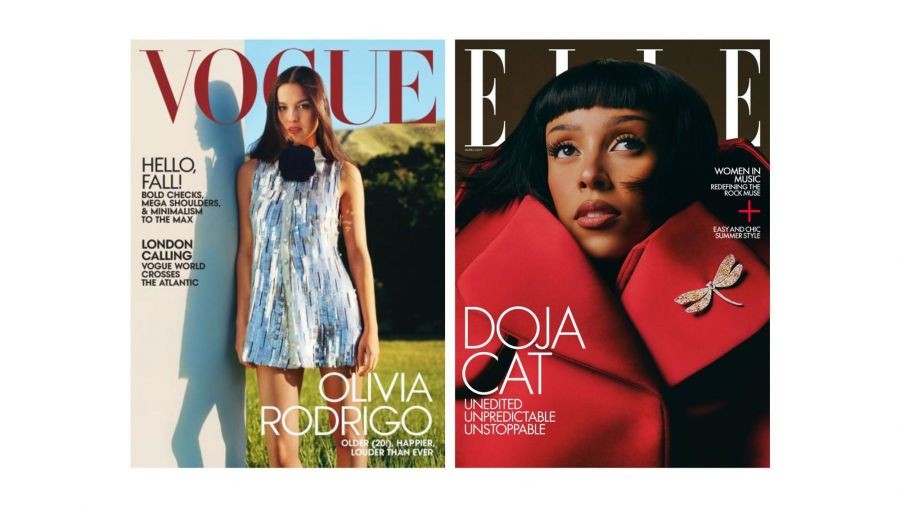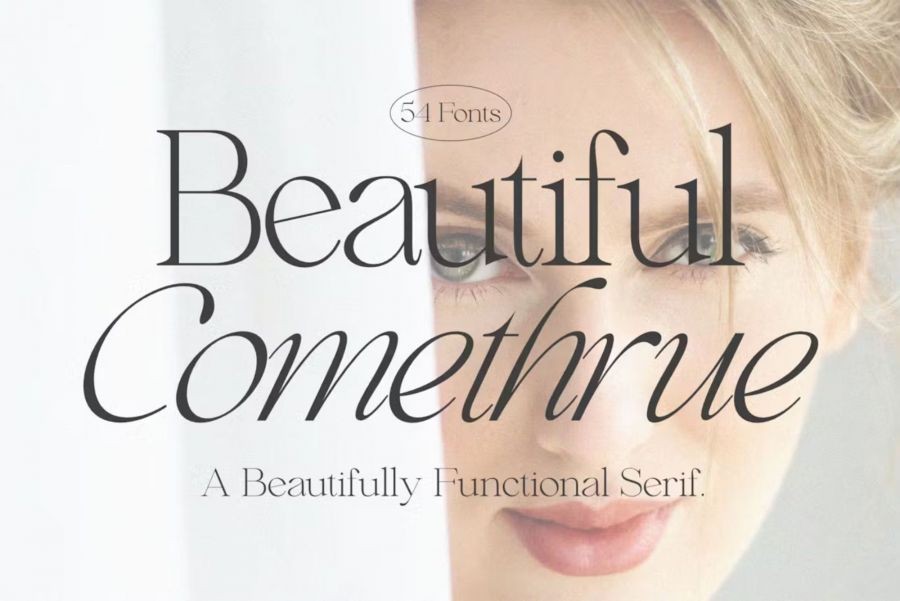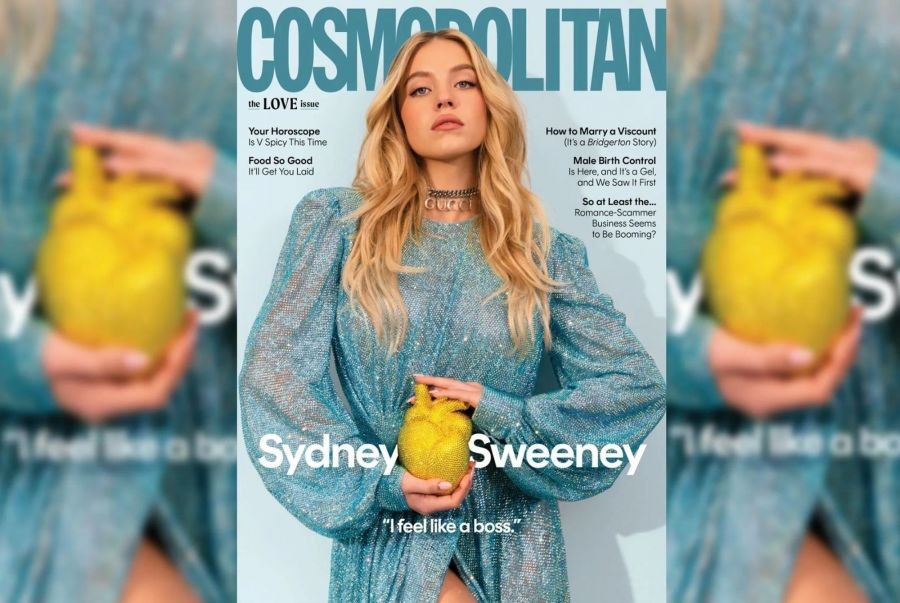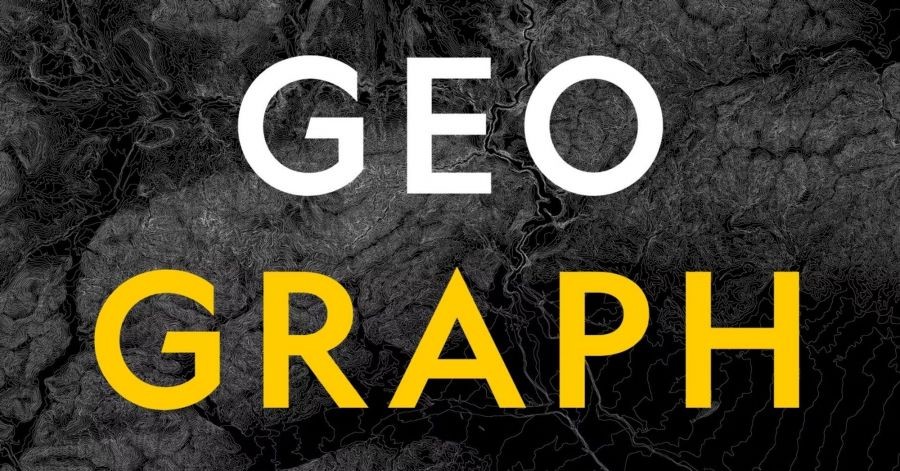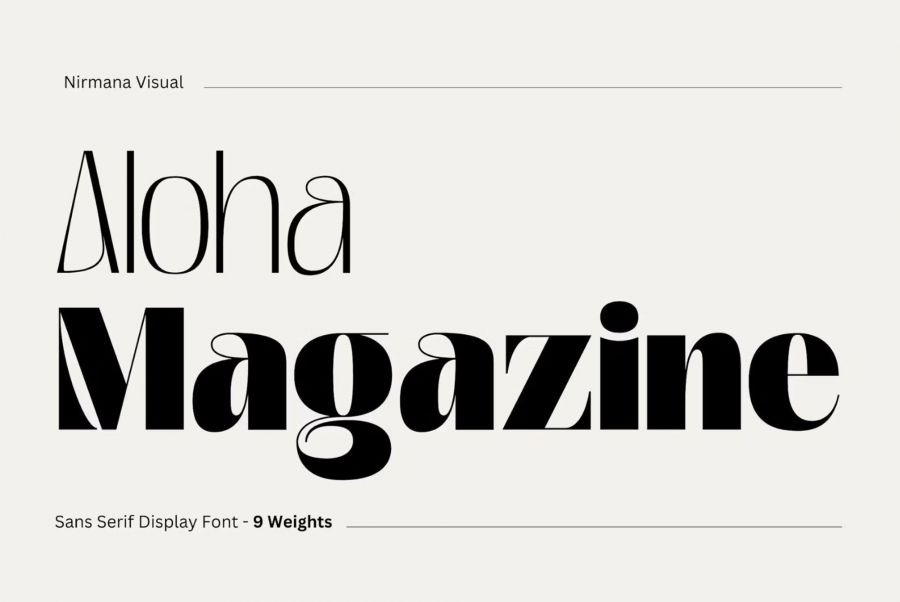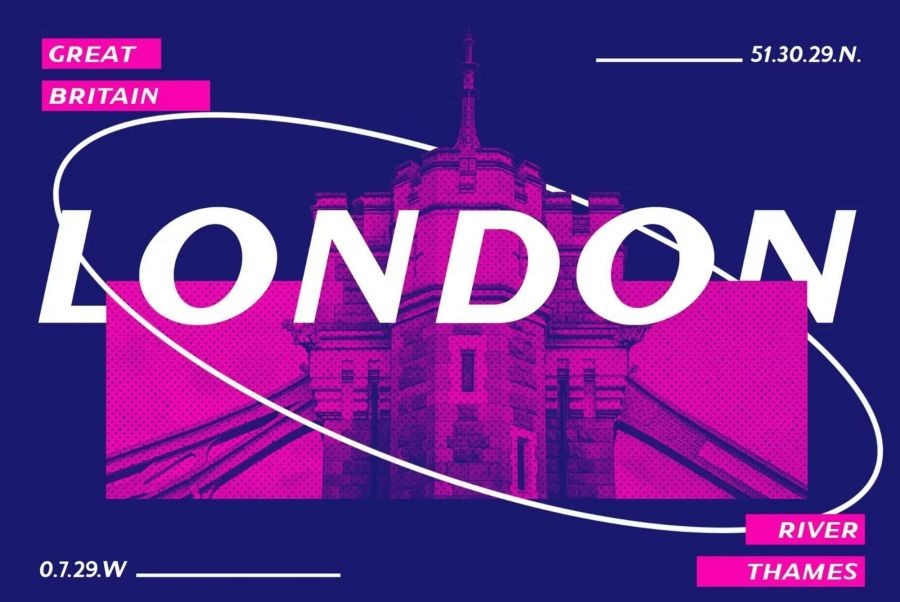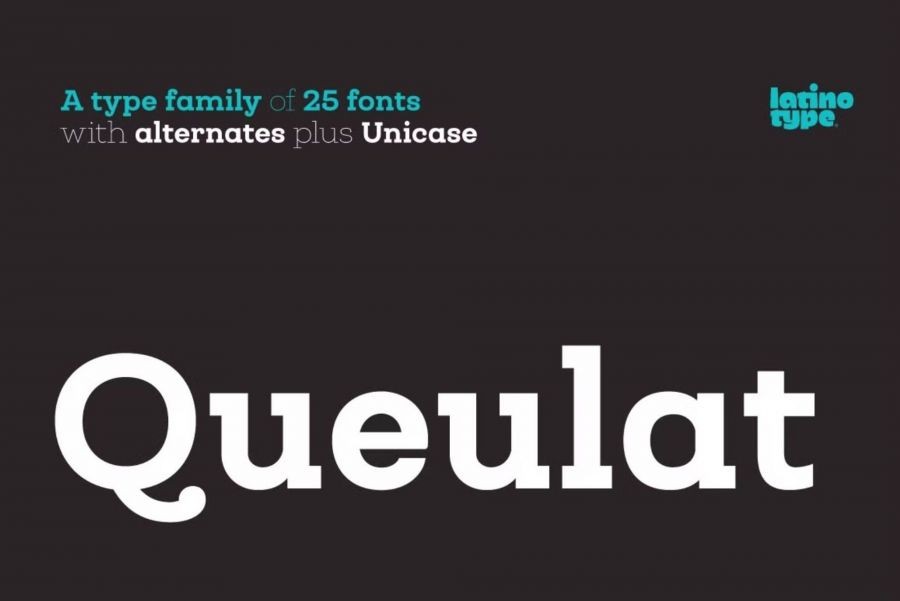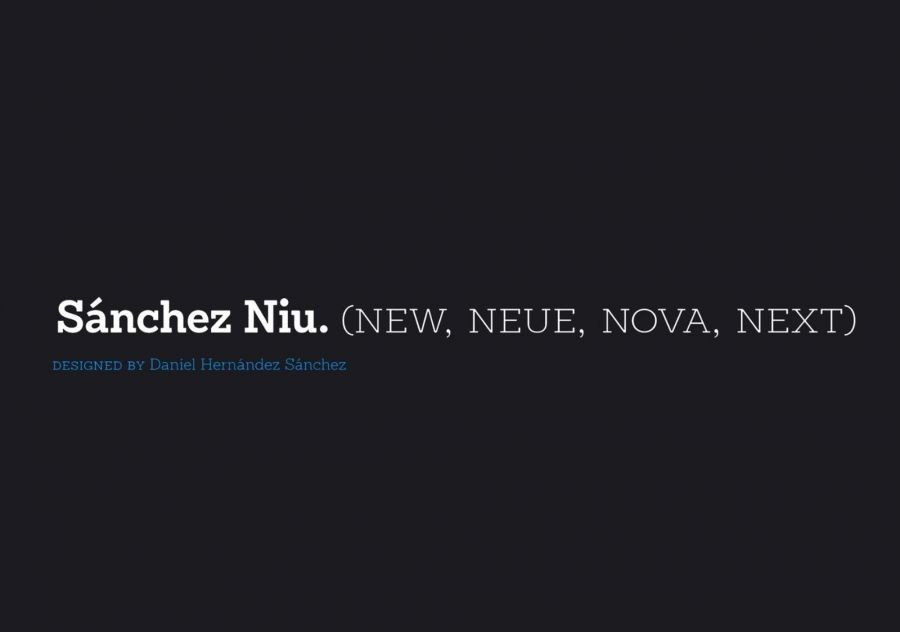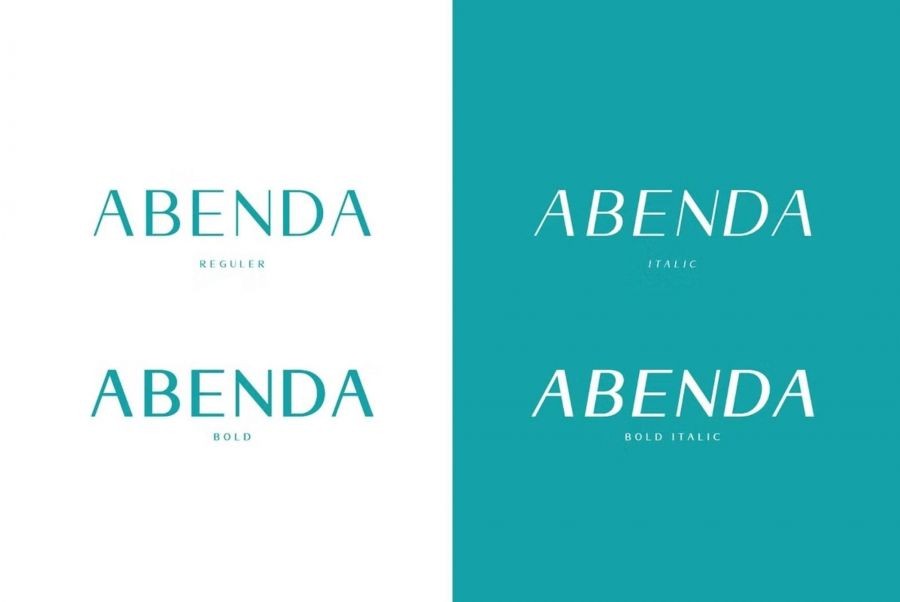
잡지 디자인에 적합한
최고의 16가지 매거진 폰트
브랜드의 개성과 콘텐츠 특성에 맞춰
시각적으로 눈에 띄고 가독성이 뛰어난
서체를 선택하는 것
잡지 디자인에 적합한
최고의 16가지 매거진 폰트 썸네일
인쇄 및 디지털 형식 모두에 가장 적합한 잡지 글꼴과 출판물에 적합한 글꼴을 선택하는 방법에 대한 팁을 알아보세요.
인기 잡지가 눈에 띄는 이유는 무엇인가요? 눈길을 사로잡는 이미지, 흥미로운 주제, 아니면 생동감 넘치는 색상 사용인가요? 이러한 모든 요소가 핵심이지만 독자의 관심을 끄는 데 중요한 역할을 하는 또 다른 요소가 있습니다. 바로 독자가 사용하는 독특한 글꼴 스타일입니다.
Vogue, Cosmo, National Geographic 등 모든 인기 잡지는 자신의 정체성, 메시지, 브랜드를 가장 잘 나타내는 글꼴을 신중하게 선택합니다. 인상적이지 않나요?
그러나 편집 디자인에 적합한 글꼴을 선택해야 할 때 작업은 그리 간단해 보이지 않습니다. 브랜드와 콘텐츠에 적합한 글꼴을 선택하는 것은 그 자체로 어려운 일입니다. 오늘은 여러분의 영감을 불러일으킬 최고의 매거진 폰트 16가지를 공유하려고 합니다. 이러한 글꼴 중 일부는 우리가 언급한 널리 알려진 잡지에서 사용되는 것과 동일한 글꼴입니다.
1. Didot Serif Typeface
Didot는 우아하고 화려해 보이기 때문에 많은 패션 잡지들이 따르는 최고의 잡지 표지 글꼴 중 하나입니다. 그러나 기사의 본문에는 적합하지 않습니다. 그 이유는 Didot가 매우 얇고 두꺼운 부분을 가지고 있어 긴 텍스트를 읽기 어려울 수 있기 때문입니다. 큰 제목이나 작은 텍스트에는 Didot를 사용하는 것이 좋습니다.
Vogue와 Elle 잡지는 패션 이슈를 돋보이게 하기 위해 이 동일한 글꼴을 선택했습니다. 가끔 잡지 이름이 표지 사진 뒤에 가려지기도 하지만, 그 스타일은 강렬하고 사람들은 여전히 그것을 알아봅니다. Elle은 또한 표지의 다른 단어에 대해 더 간단한 버전의 Didot 글꼴을 사용합니다. 이를 통해 독자는 주요 텍스트가 현대적인 Serif 글꼴 로 되어 있어 어떤 부분이 가장 중요한지 알 수 있습니다 .
2. Franklin Gothic Extra Condensed
Cosmopolitan 잡지 로고는 Franklin Gothic Extra Condensed라는 산세리프 글꼴을 사용합니다. 1902년에 American Type Founders라는 그룹을 위해 Morris Fuller Benton이라는 디자이너가 만들었습니다.
이 글꼴은 큰 제목과 로고 모두에 적합합니다. 강렬하고 상큼한 모습이 돋보이는데요. 또한 대담한 스타일 덕분에 뷰티, 유명인 가십, 뉴스 등 모든 종류의 잡지에 사용할 수 있습니다.
3. Geograph
지오그래프(Geograph)는 노란색 테두리가 있는 잡지 서체로 유명한 내셔널 지오그래픽(National Geographic)에서 사용하는 주요 글꼴입니다.
Geograph는 내셔널 지오그래픽만이 사용할 수 있는 특수 글꼴이므로 다른 사람은 자신의 프로젝트에 사용할 수 없습니다. 하지만 이 글꼴은 선명하고 날카로운 선이 있으며 어디에서나 사용되는 잘 알려진 Futura 글꼴과 같은 모양과 느낌을 갖도록 디자인되었습니다. Futura는 매우 다재다능하기 때문에 로고, 제목, 표제 생성과 같이 깔끔하고 기하학적인 모양이 필요한 거의 모든 작업에 사용할 수 있습니다. 잡지 본문 텍스트에 가장 적합한 글꼴이기도 합니다.
4. Bodoni
Bodoni는 확실히 잡지 레이아웃에 적합한 글꼴입니다. 자동차 잡지든 비즈니스 잡지든 상관없이 Bodoni는 선택할 수 있는 다양한 스타일을 제공합니다. 헤드라인, 로고, 멋진 텍스트까지 돋보이게 만드는 데 적합합니다.
5. Saint Capital Modern
Saint Capital Modern은 New York 잡지에서 볼 수 있는 것과 유사한 재미 있고 낙관적이며 세련된 글꼴입니다. 올드스쿨 스타일과 심플하고 모던한 스타일이 결합되어 있습니다. 이는 다양한 잡지, 특히 뉴스 기사를 공유하는 잡지에 적합합니다.
이 글꼴은 관심을 끄는 제목과 표제를 만드는 데 적합할 뿐만 아니라 전체 디자인에 세련미를 더하는 데도 좋습니다. 다양한 크기와 무게로 사용할 수 있는 다용도 글꼴로 인쇄 매체와 디지털 매체 모두에 적합합니다.
6. Girly Moods Script
10대 잡지에 여성스럽거나 페미니스트적인 느낌을 주는 글꼴 모음이 필요하다면 Girly Moods Script가 바로 그것입니다! 청소년을 대상으로 한 프로젝트에 귀엽고 완벽한 선택입니다.
Girly Moods Script는 손글씨처럼 보이는 재미있고 예술적인 글꼴입니다. 매우 유연하여 잡지 표지, 브랜드, 기사 및 주요 제목과 같은 항목에 적합합니다. 다양한 언어를 지원하고 특수 문자가 많아 진정성 있고 매력적인 모습을 보여줍니다.
7. Aloha Sans Serif Magazine Font
Aloha Magazine은 로고, 브랜딩, 소셜 미디어 게시물, 광고, 제품 디자인 등 다양한 디자인 요구 사항에 적합합니다. 그것은 모든 것을 멋지게 조합하고 매력적으로 보이게 만듭니다. 이 글꼴은 깨끗하고 현대적이며 우아합니다. 친근하고 매력적인 느낌을 주는 아름다운 손글씨 스타일이 있습니다.
8. NY Irvin
NY Irvin은 Wiescher Design에서 제작한 단순하고 깨끗하며 아름다운 세리프 글꼴입니다. 좋은 점은 해당 버전을 무료로 얻을 수 있다는 것입니다.
그러나 NY Irvin은 완벽한 조화를 이루는 Adobe Caslon Pro가 없으면 완전하지 않습니다. 이 현대적인 산세리프 글꼴은 The New Yorker가 기사에 사용하는 또 다른 인기 글꼴 입니다. Carol Twombly가 디자인한 이 책은 잡지 전체에 고급스러운 느낌을 더해줍니다.
9. Magneticot
Montserrat는 Julieta Ulanovsky가 2011년에 만든 간단한 모양 기반 글꼴입니다. Julieta는 Montserrat라고도 불리는 부에노스아이레스의 오래되고 역사적인 지역에 있는 간판과 포스터에서 아이디어를 얻었습니다.
Montserrat는 따라하기 쉽게 깔끔하고 정돈된 모양을 갖추고 있어 라이프스타일이나 웨딩 잡지의 제목, 부제목, 대량의 일반 텍스트 등에 적합합니다.
10. Magnetico
완벽한 글꼴, 로고, 제목, 큰 제목 또는 인용문과 같은 잡지의 특정 부분을 돋보이게 할 수 있는 글꼴을 찾고 계시나요? Magnetico는 진정으로 관심을 끄는 글꼴입니다.
Magnetico는 이탤릭체 산세리프 서체입니다. 매우 모던한 느낌을 주며 독자들에게 차분하고 편안한 느낌을 주기 때문에 라이프스타일, 홈 데코, 인테리어 디자인 등 모든 종류의 잡지에 인기가 높습니다.
11. Queulat
정말 눈에 띄는 완벽한 잡지 글꼴을 원한다면 Queulat을 살펴보세요. 두 가지 다른 모양을 혼합한 독특한 종류의 글꼴입니다. 하나는 간단하고 다른 하나는 좀 더 장식적입니다.
독특한 모양을 지닌 이 글꼴의 제작자는 브랜드 로고 디자인 및 제품 패키지과 같은 곳에 완벽함을 보장합니다.
12. Sanchez Niu
2011년에 Latinotype 팀은 Sanchez라는 유명한 세리프 글꼴을 만들었습니다. 그런 다음 Sanchez Niu라는 새 버전을 만들었습니다. 이 업데이트된 버전은 긴 텍스트에 더 적합합니다. 원본과 많이 비슷해 보이지만 모양이 조금 다르고 새로운 글자도 있습니다.
Sanchez Niu는 대담하면서도 우아한 외관을 갖고 있어 헤드라인과 소제목을 위한 훌륭한 선택이기도 합니다. 그 다양성으로 인해 현대적인 디자인과 전통적인 디자인 모두에 적합합니다.
13. Abenda
아벤다(Abenda)는 1920년대 아르데코 트렌드 를 연상시키기 위해 디자인된 글꼴 유형입니다 . '광란의 20대'의 신나고 대담한 룩과 모던하고 부드러운 모습이 어우러져 있다. 작업이 간편하고 잡지 글꼴에 대한 최고의 선택 중 하나가 되는 특별한 손길을 가지고 있기 때문에 눈에 띕니다.
14. Biomorph
Biomorph는 브랜드 아이덴티티 생성, 출판 자료, 헤드라인, 서적, 잡지, 웹사이트 등 모든 종류의 프로젝트에 적합한 슬림하고 매끄러운 산세리프 글꼴입니다. 이 응축된 산세리프 글꼴 모음은 매우 얇은 것부터 굵은 것까지 다양한 두께를 제공하므로 디자인을 돋보이게 할 수 있는 다양한 옵션을 제공합니다.
15. Beautiful Comethrue
에디토리얼 작품이나 여성스러운 제품을 디자인할 때 Beautiful Comethrue 글꼴 모음을 놓칠 수 없습니다. 우아한 터치가 돋보이는 사랑스럽고 모던한 세리프 서체로, 세련미와 여성성을 전달하고 싶은 디자인에 적합합니다.
16. Boston Village
보스턴 빌리지(Boston Village)는 다소 낡아 보이면서도 스타일리쉬한 심플하고 우아하며 모던한 글꼴입니다. 읽기 쉽고 다양한 언어를 지원합니다. 이 글꼴은 매우 유연하여 크고 작은 것 모두 보기에 좋습니다. 브랜드 로고 만들기, 의류 라벨 디자인, 제품 패키지, 잡지 제목, 사진 위에 화려한 텍스트 추가 등에 적합합니다.
잡지 디자인을 위한 글꼴 선택
잡지는 시각적인 내용이 많기 때문에 매력적이고 매력적인 디자인을 만들려면 올바른 글꼴을 선택하는 것이 중요합니다. 다음은 잡지 서체를 선택할 때 염두에 두어야 할 몇 가지 팁입니다.